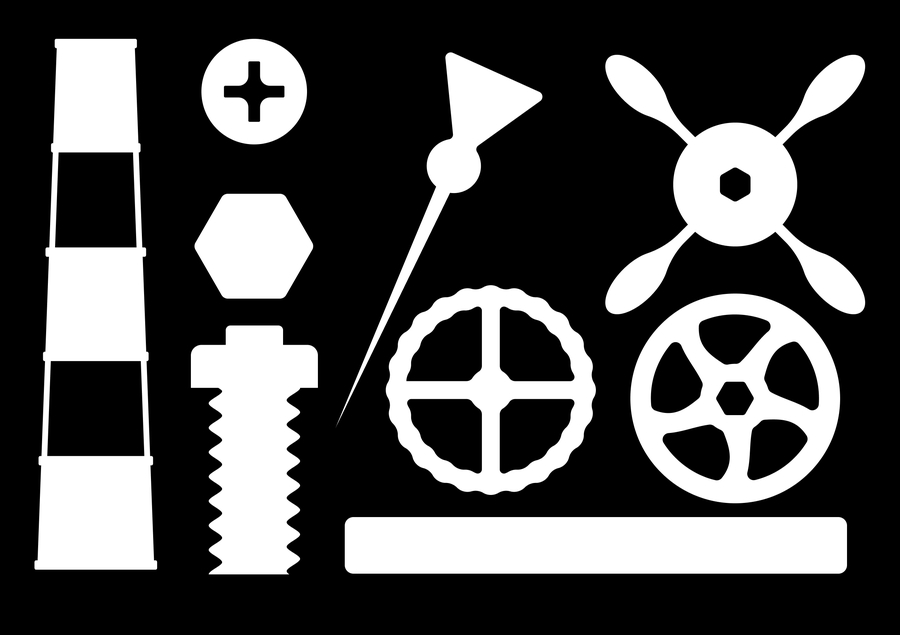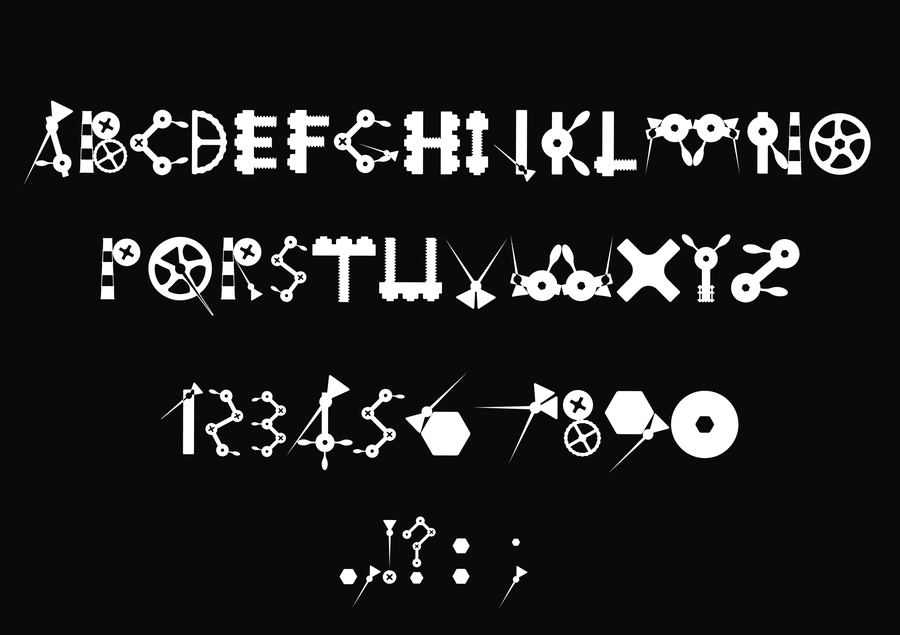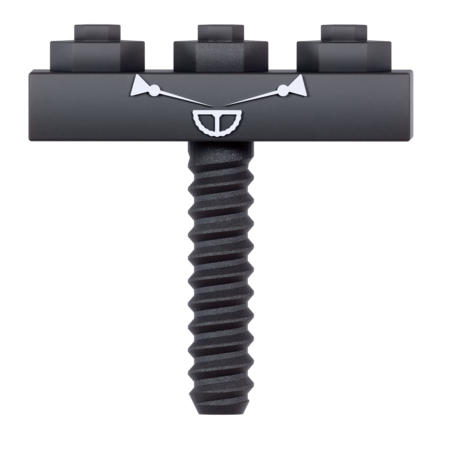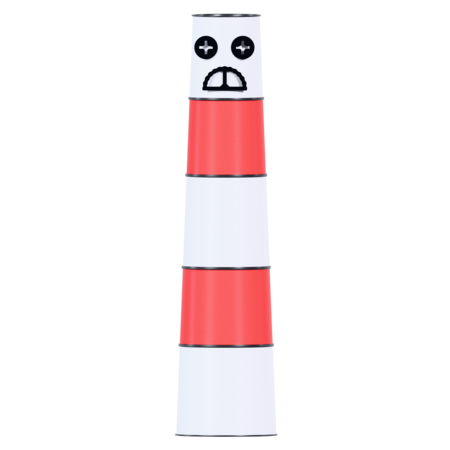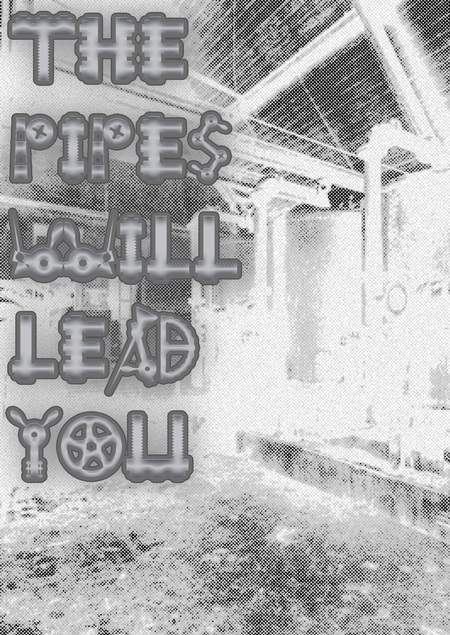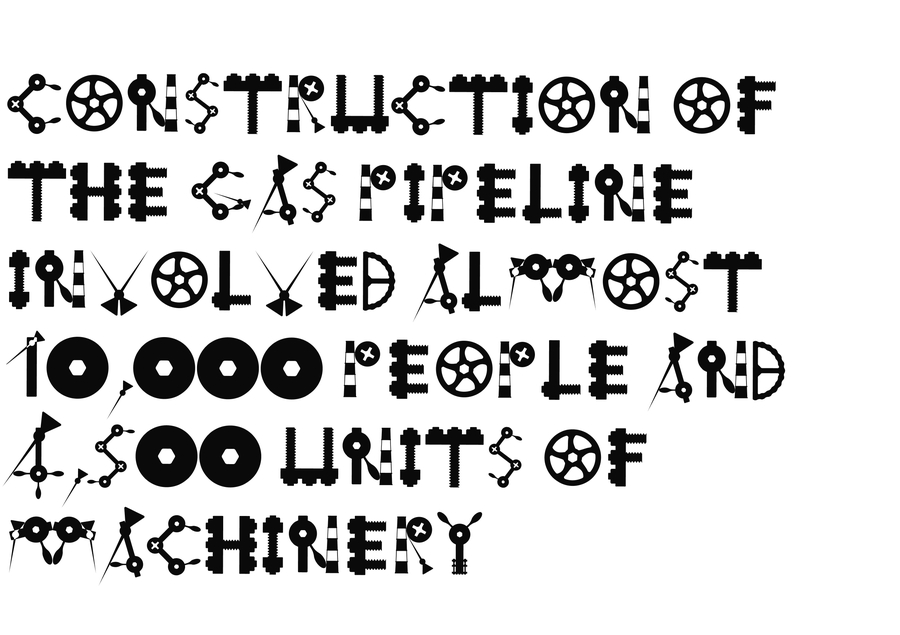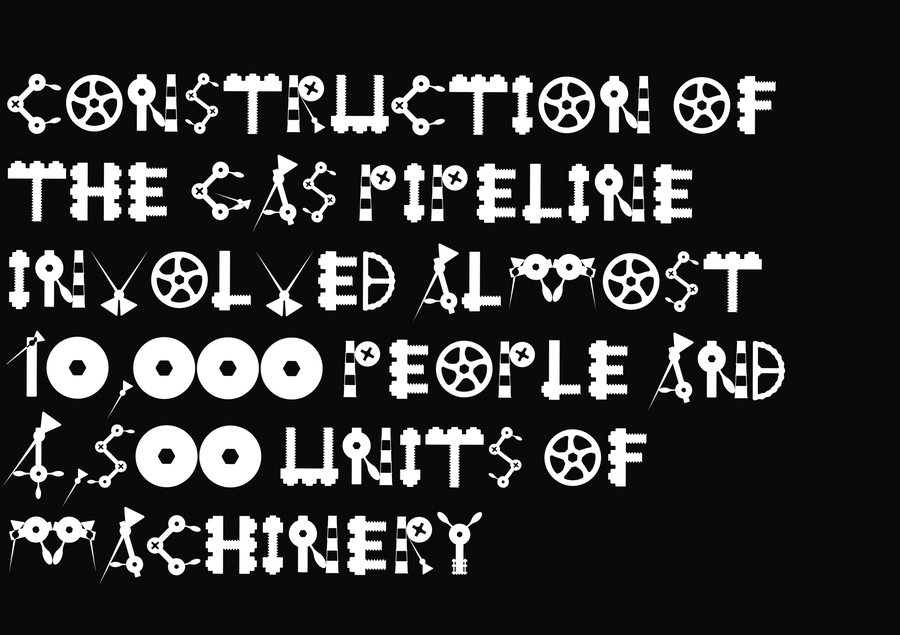
как-то раз я попал в бесхозную котельню и вынес оттуда пару модулей для своего акцидентного шрифта KOTEL’NYA.
модули
все части так или иначе связаны с трубопроводом и являются частью его экосистемы
шрифтовая касса
набор
носители
следуй за трубами.
детская интерактивная игрушка — PIPESMASH
PIPESMASH представляет из себя переработку детской игры, где нужно вовремя ударить по выпрыгивающим лягушкам резиновым молоточком.
Только тут нужно бить по усталым трубам
ПЕРСОНАЖИ — заводной резиновый молот // усталая труба
процесс игры
упаковка